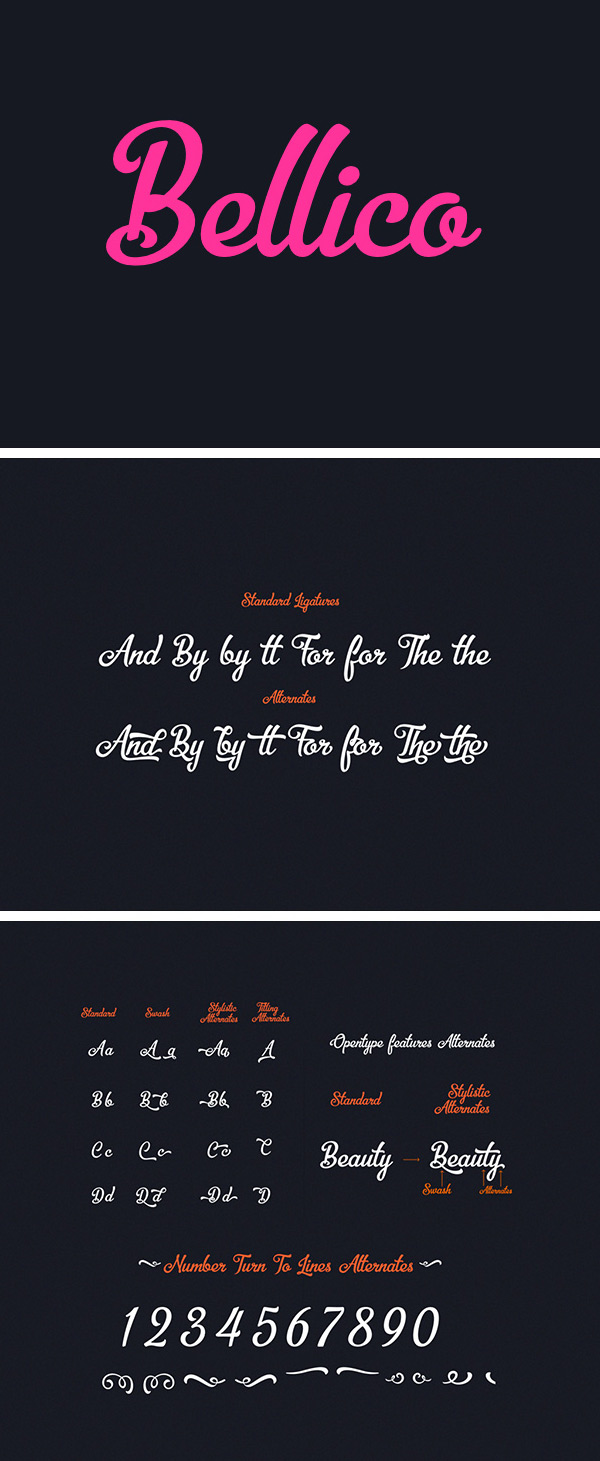
Автору спасибо, шрифт очень красивый!:) Только не пойму как переключать цифры на эти завитушки. Подскажите, пожалуйста, очень нужно!!!
Шрифт красивый, особенно если применять градиент. Спасибо.
Есть русский язык?